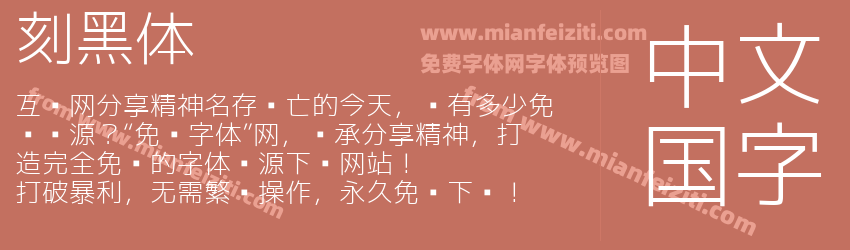
刻黑体
刻黑体是一种结合了标准黑体字体与相矛盾的小平假名和片假名字符的字体。 与传统的平假名和片假名相比,线性形状是一个特征。 汉字的设计水平图像比垂直图像略薄。 这表达了一种轻盈而有节奏的氛围。
平假名和片假名保留其独特的形状,但不追求过于具体的设计,从而带来清新的效果。 合理平滑的曲线给人一种安全和稳定的感觉。 虽然假名与一般字体有很大不同,但它的设计目的是保留每个识别字符的特性,以免降低可读性。
本款“刻黑体”是一款书写很新颖的字体,字体大方,适合各种设计作品使用!欢迎下载!